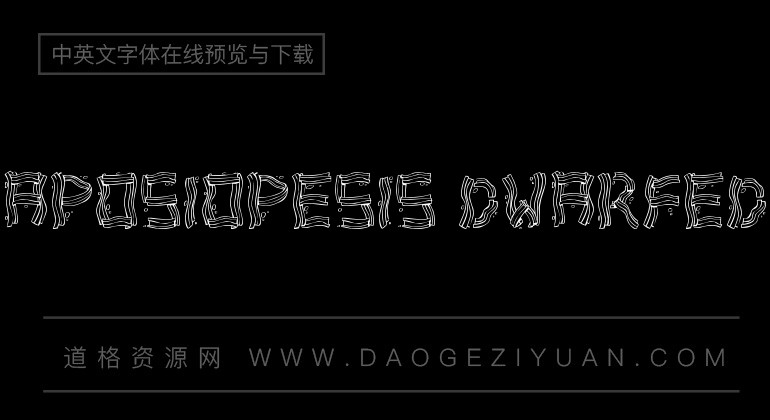
? Aposiopesis Dwarfed 是一款由英国设计师Rian Hughes设计的字体,它有着独特的外观和非凡的细节,这使它成为一款非常独特的字体。它的字形极具特色,充满了古典的风格,其中的每一个字形都十分精致,有着精细的线条和曲线,这使它能够很好地表达文字的精髓。它的字体类型有着较大的差异,可以满足不同的设计需求,可以用于海报、标志、书籍封面等设计。内容介绍
Aposiopesis Dwarfed是一款非常不错的手写艺术字体,具有很好的视觉感,适合于文化类的宣传设计、商业类品牌的广告和产品包装设计以及个性化文字排版等较多场景。